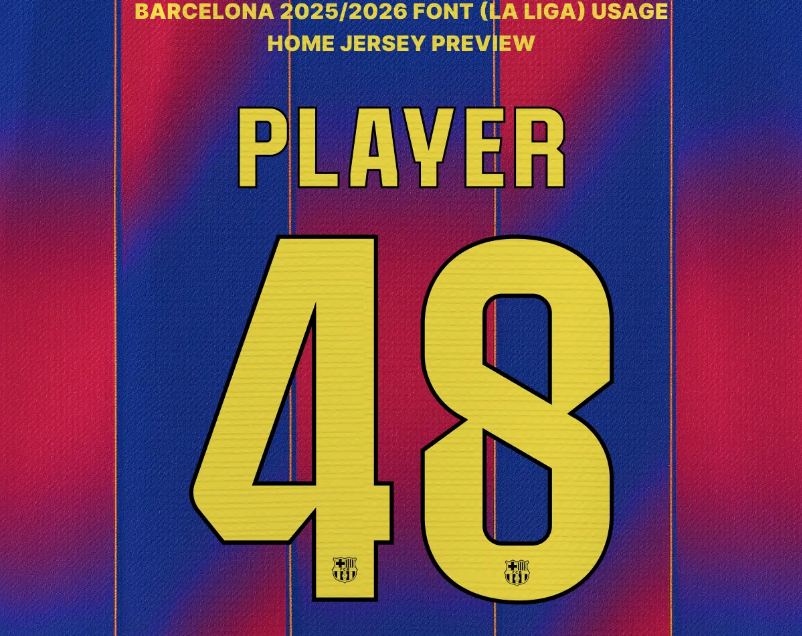
Fonte FC Barcelona 2025/26 (Nike) – Download TTF e Vetor para Personalização
A parceria histórica entre o FC Barcelona e a Nike continua ditando tendências no futebol mundial. Para a temporada 2025/2026, o clube catalão apresenta uma identidade visual que reflete a modernidade do novo Spotify Camp Nou, sem perder a essência das cores Blaugrana.
Estilo Visual e Aplicação
A fonte 2025/26 do Barcelona aposta em um design geométrico com cortes incisivos, transmitindo velocidade e dinamismo. A Nike buscou inspiração na arquitetura de Barcelona, resultando em números com peso visual equilibrado e excelente legibilidade à distância.
É importante notar que esta é a “Cup Font” (Fonte de Copas). Enquanto na La Liga o clube utiliza a tipografia padronizada da liga, é com esta fonte exclusiva que o time brilha nos palcos da UEFA Champions League e na Copa do Rei. Ela é perfeita para estampar nomes de craques como Lamine Yamal, Pedri e Gavi nas camisas Titular (Home), Reserva (Away) e no Terceiro Uniforme (Third).
Dica de Especialista: Para estamparia em camisas escuras, utilize o contorno (stroke) na cor contrastante (geralmente amarelo ou dourado) para replicar fielmente o efeito oficial usado pelos jogadores.